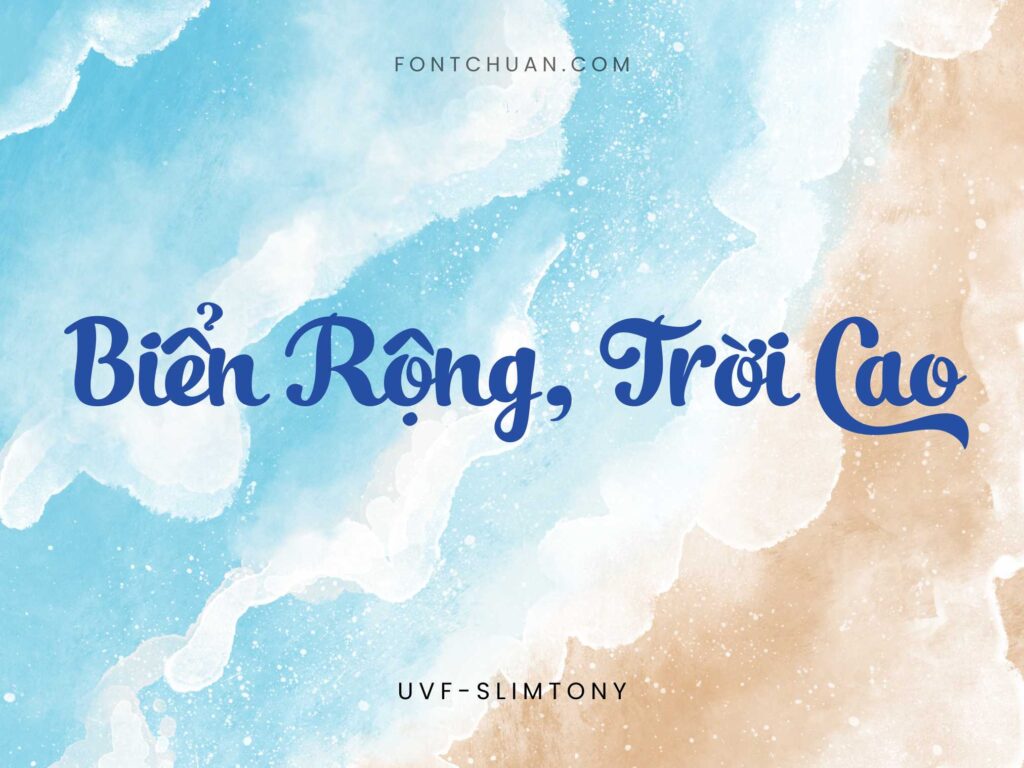
Font UVF Slim Tony Việt Hóa
Slim Tony là một phông chữ script đẹp mắt, được thiết kế bởi Fenotype. Phông chữ này là “họ hàng xa” của Mishka nhưng táo bạo và ngông cuồng hơn nhiều. Slim Tony hoạt động tuyệt vời cho các tiêu đề và biểu trưng tùy chỉnh. Bật Swash, Stylistic hoặc Contextual Alternates để có thêm một số cú hích nghiêm trọng. Phông chữ này đã được Việt hóa, hỗ trợ đầy đủ các ký tự tiếng Việt, giúp người dùng tại Việt Nam dễ dàng sử dụng trong các dự án sáng tạo của mình.
Với thiết kế độc đáo và nghệ thuật, Slim Tony phù hợp cho các ứng dụng như thiệp mời, logo thương hiệu cao cấp, bìa sách hoặc các ấn phẩm đặc biệt, nơi cần tạo ra sự ấn tượng mạnh mẽ về thị giác và cảm xúc. Trong lĩnh vực sự kiện, phông chữ này có thể được sử dụng trong các dịp như lễ hội, lễ cưới và các sự kiện văn hóa. Ngoài ra, Slim Tony cũng thích hợp cho các ngành nghề như thiết kế đồ họa, nghệ thuật trang trí và xuất bản.